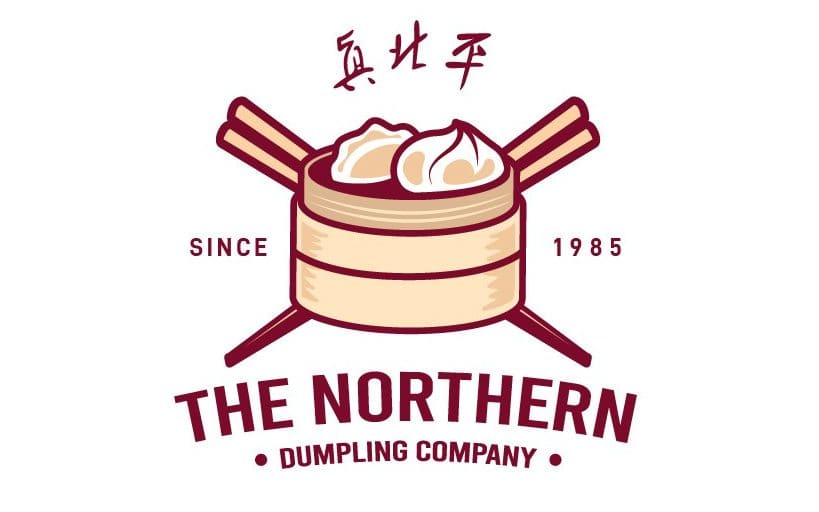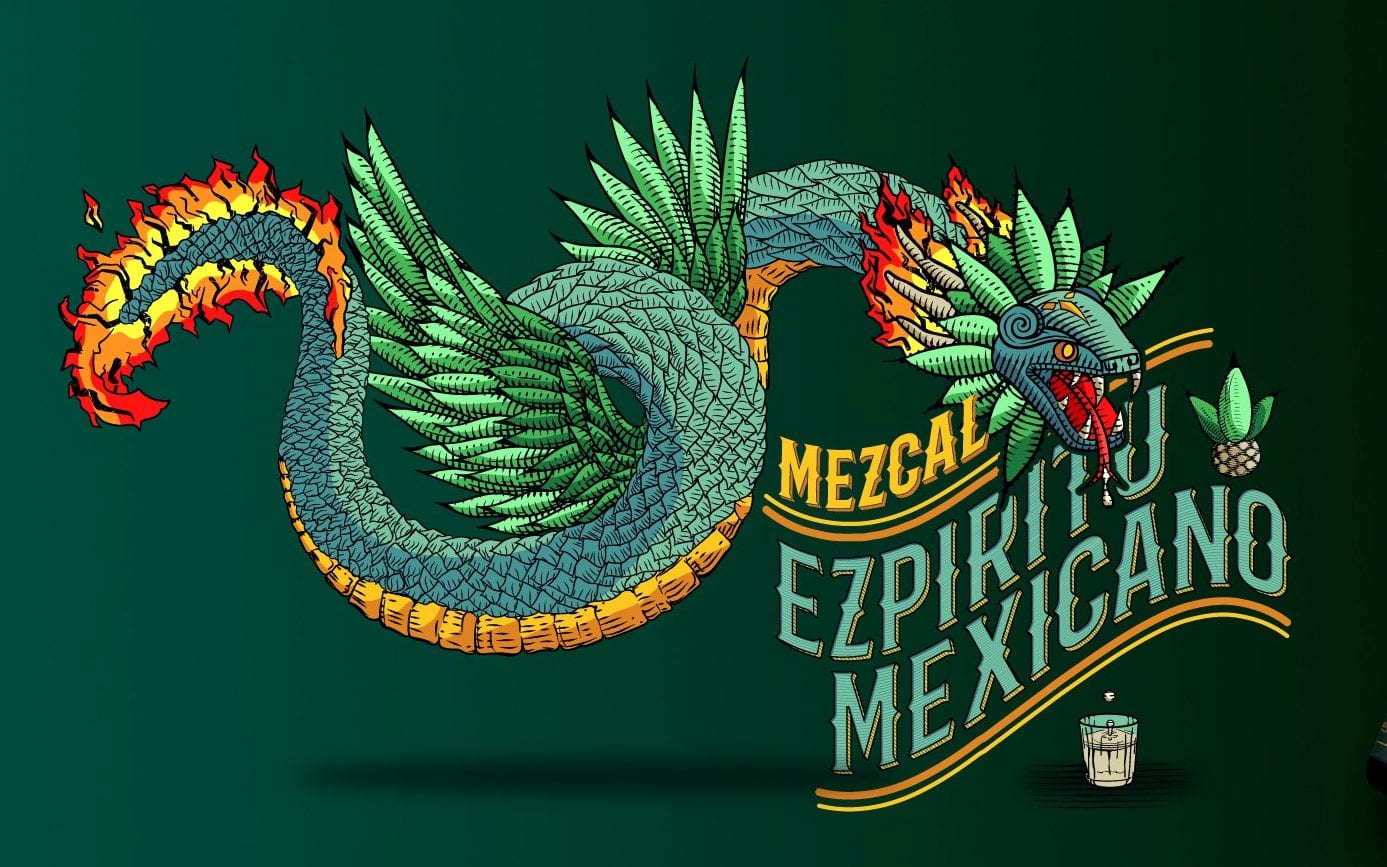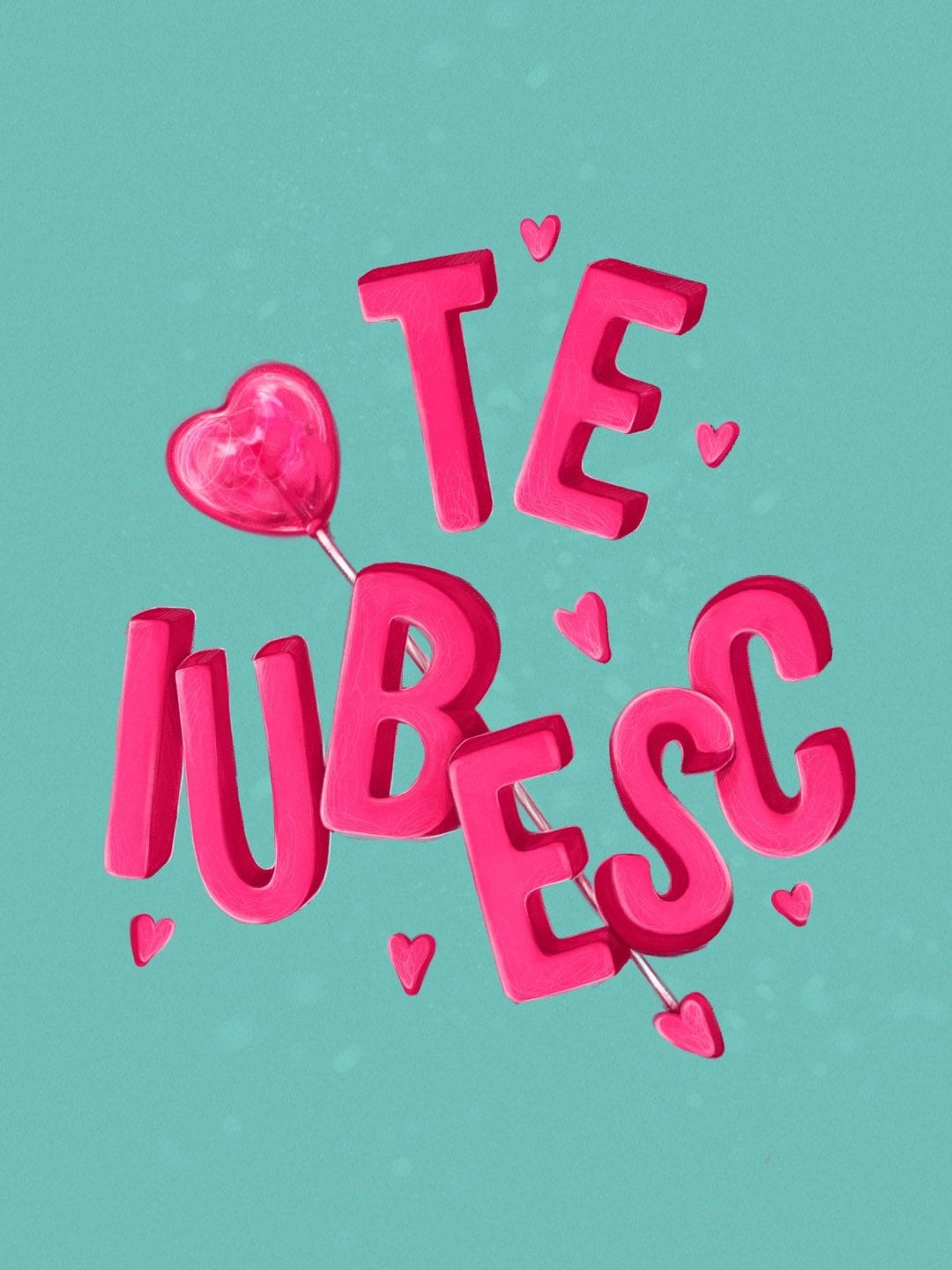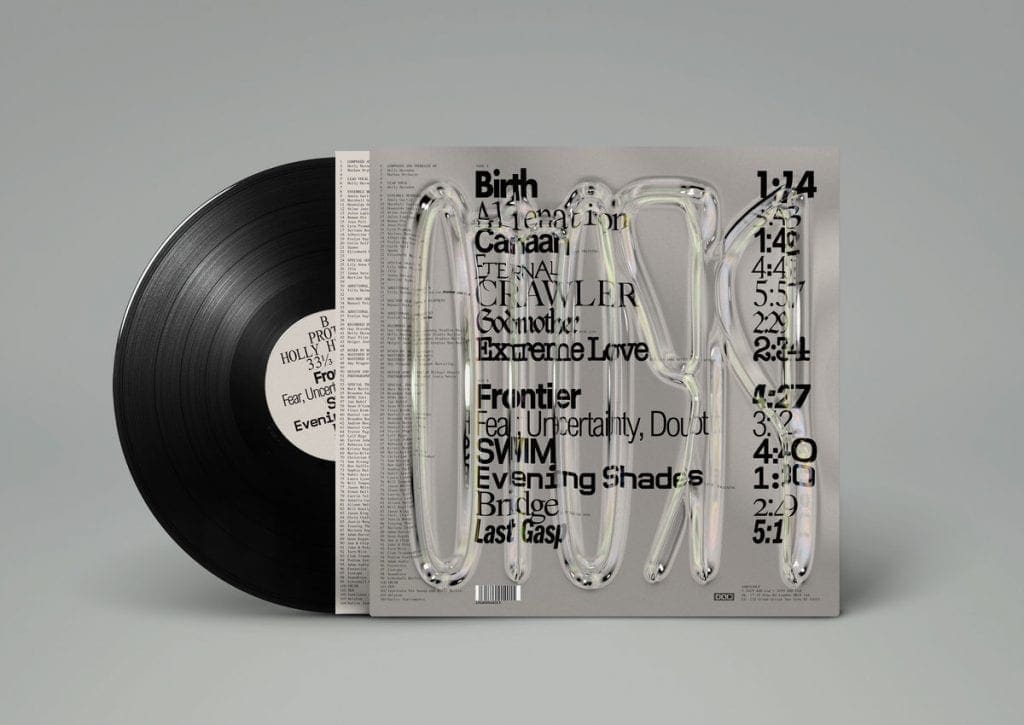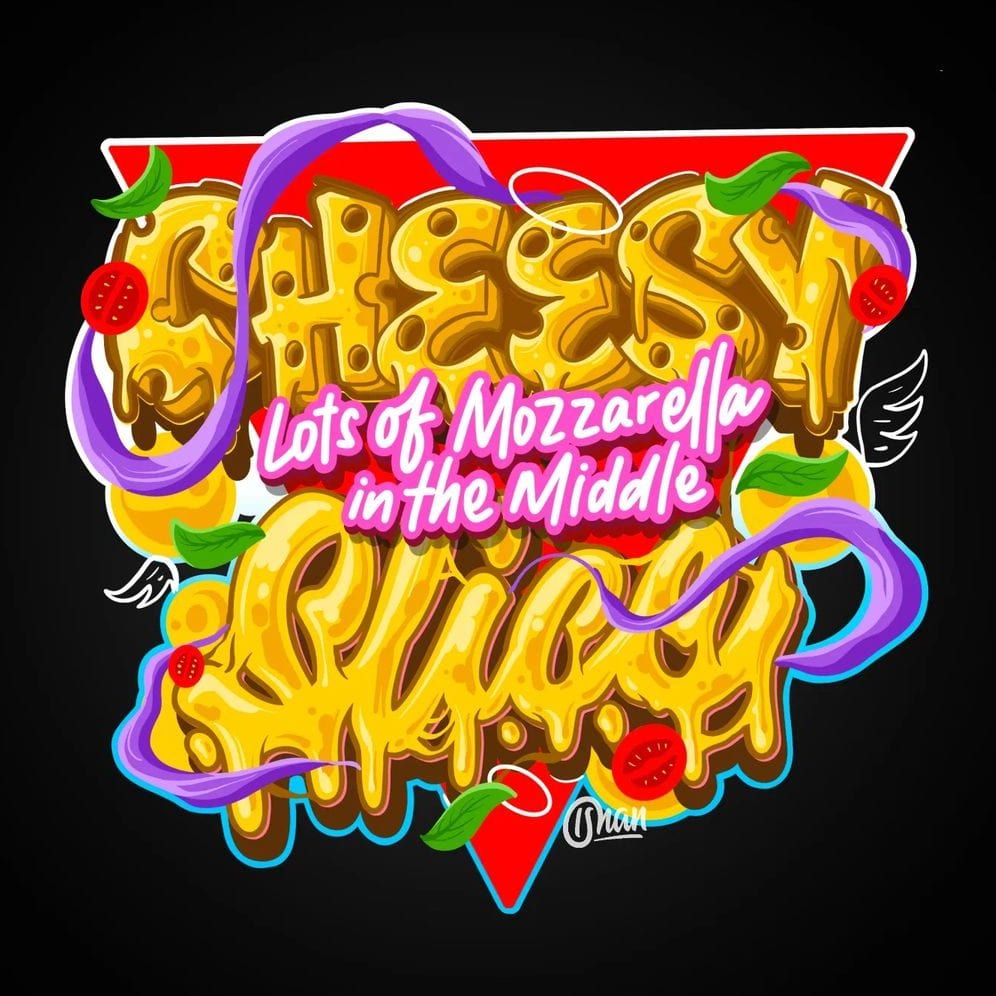
Aktuell erlebt die digitale Kunstwelt eine einzigartige Phase der Transition. Die Schriftarten-Trends für 2024 spiegeln das wider. Vor dem sich schnell ändernden Hintergrund aus maschinellem Lernen und generativer KI haben sich viele Schriftartenentwicklerinnen und -entwickler auf traditionelle handschriftliche Techniken zurückbesonnen. Gleichzeitig treibt eine neue Designergeneration die Schriftarten in kreative Extreme: mit Buchstaben, die sich bewegen, Platz beanspruchen und ins Abstrakte abdriften.
Wir stellen sieben Schriftarten-Trends für das Jahr 2024 vor – unabhängig vom Designansatz entspringen sie alle der Kreativität von Typografinnen und Typografen im beispiellosen digitalen Zeitalter. Ob Sie einen neu aufgelegten Retro-Stil bevorzugen oder auf knallige Experimente setzen möchten, diese Schriftarten sprechen Leserinnen und Leser weit über die geschriebenen Worte hinaus an. Und sie bieten Kleinunternehmen neue Möglichkeiten, Ihre Marke oder Perspektive auf diese neue Welt visuell umzusetzen.
Top 7 Schriftarten-Trends für 2024
1. Ultra Gothic
Fraktur-Schriftarten sind wahre Klassiker. Sie wurden im Mittelalter für handschriftliche Abschriften entwickelt. Die traditionelle Fraktur besteht aus dicken schwarzen Buchstaben und zeichnet sich durch Kalligrafietechniken wie Schnörkel (den sogenannten Elefantenrüssel) und kantige Striche aus. Die an die Spitzbögen mittelalterlicher Klöster erinnernden Fraktur-Schriftarten erfreuen sich anhaltender Beliebtheit. Erst im letzten Jahr wurde der „Ultra Gothic“-Trend massentauglich und heute erfährt er einen neuen Boost.
Beim „Ultra Gothic“-Trend 2024 verwenden Designerinnen und Designer digitale Hilfsmittel, um Effekte zu erzielen, die mit der klassischen Schriftartenkreation nicht möglich waren. Übertriebene Striche und Linien halten mit der faszinierenden mittelalterlichen Architektur Schritt und komplexe Schnörkel grenzen an Unleserlichkeit. Fraktur-Schriftarten sind zeitlos attraktiv aufgrund ihres charakteristischen Stils, der stabile Formen mit unerwarteten Freihandstrichen kombiniert, was digitalen Schriftarten einen persönlichen Touch gibt. Und obwohl die Fraktur-Schriftarten Konnotationen aus der alten Welt mitbringen, passen ihre abenteuerlichen Schnörkel doch perfekt in Magazin-Typografie und Logodesign-Schriften.
„Neo Gothic ist bereits ein Trend in der Architektur und Literatur und gewinnt im zeitgenössischen Design an Bedeutung, wo er durch die Verwendung von Ornamenten, Schwarzschrift und Kalligraphie in wundervolle Schriftbilder umgesetzt wird. Dieser Stil passt zu High-End-Produkten und Luxusmarken. Er kann aber auch cool und urban umgesetzt werden, zum Beispiel kombiniert mit Graffiti- und Street-Art-Elementen.“
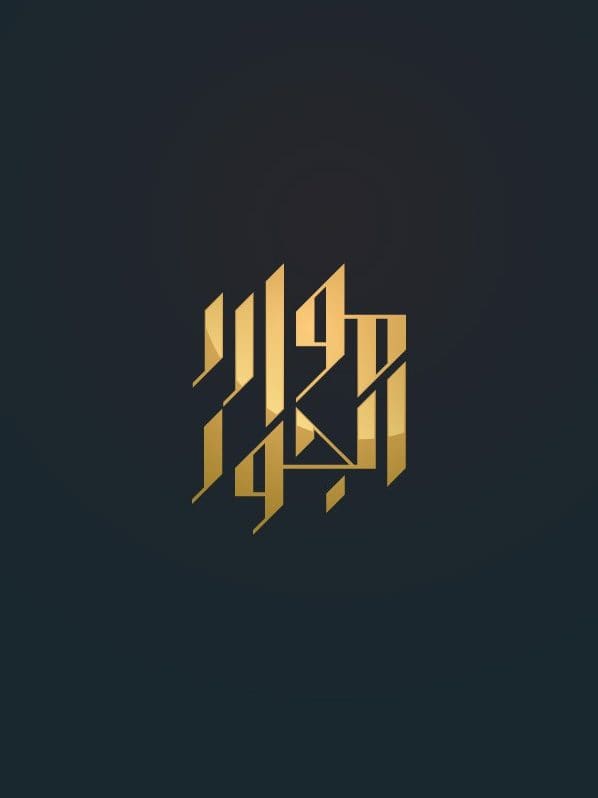
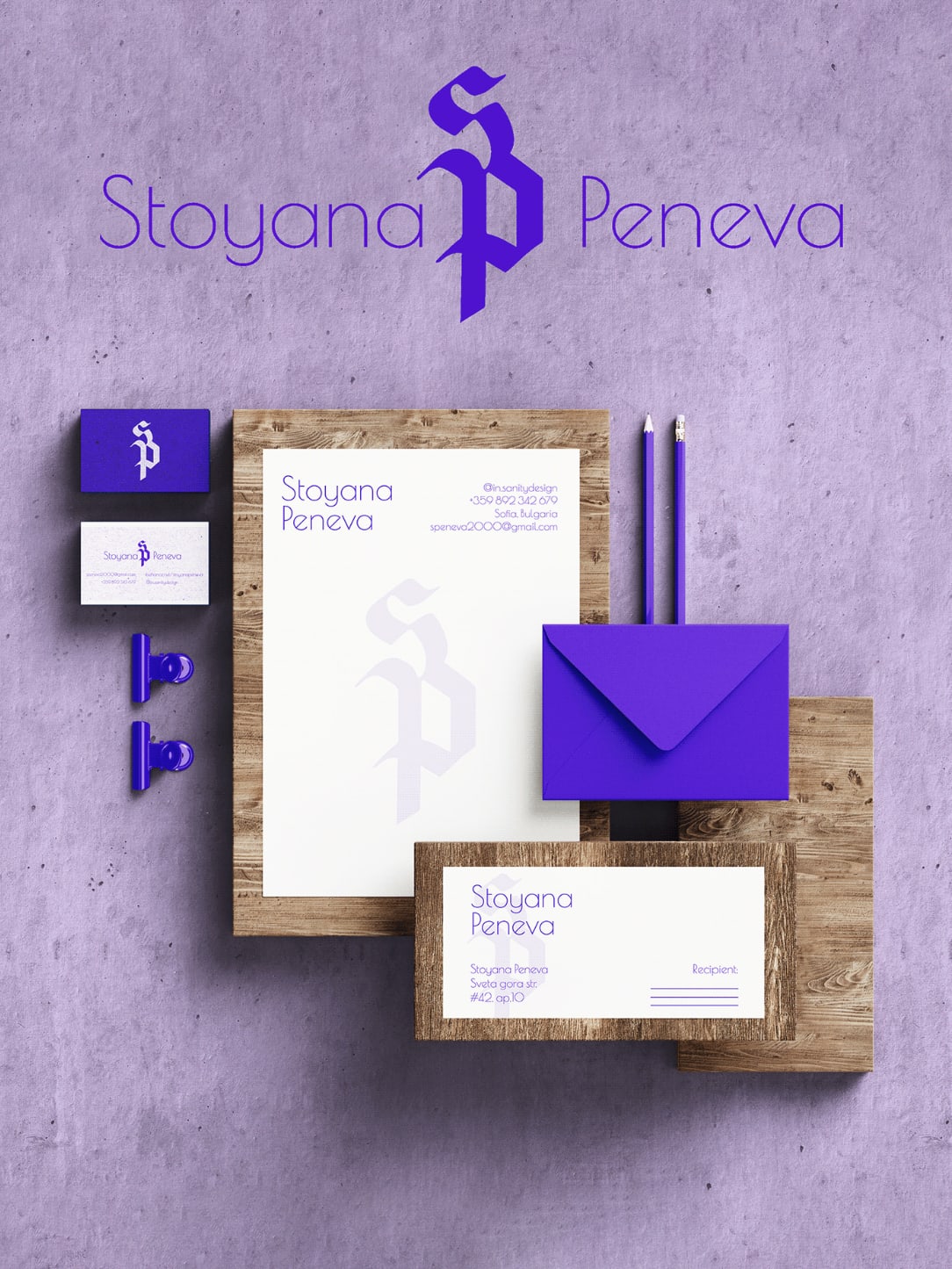
2. Formverändernde Buchstaben
Was wir aus der Tatsache lernen, dass Schriftartendesignerinnen und -designer aus ein und demselben Alphabet unendlich viele Buchstabenvariationen zaubern können, ist, dass Buchstaben unglaublich wandelbar sind. Und 2024 werden wir Schriftarten entdecken, die ihre Form direkt vor unseren Augen verändern.
Der Trend der formverändernden Buchstaben ist von Retro-Quellen inspiriert, wie Rubberhose-Schriften und Comic- und Cartoon-Styles aus den 70ern. In diesem Sinne ruft der Trend nostalgische Gefühle hervor und erweckt die Vergangenheit durch fließende Bewegungen zum Leben. Die schmelzende Form der wabbeligen Buchstaben deutet an, dass hier etwas nicht stimmt – eine leicht verzerrte Realitätsflucht.
Dem Eskapismus wohnt eine Spannung inne, denn auch wenn er uns an einen glücklichen Ort aus der Vergangenheit entfliehen lässt, impliziert das Bedürfnis nach einer Flucht, dass es etwas gibt, vor dem man fliehen muss. Solche Schriftarten spielen mit dieser Spannung in einem comicartigen Cartoon-Style und machen den Trend damit für provokantere Kontexte beliebt, wie Poster für Musikevents, Streetwear und Protestkunst.
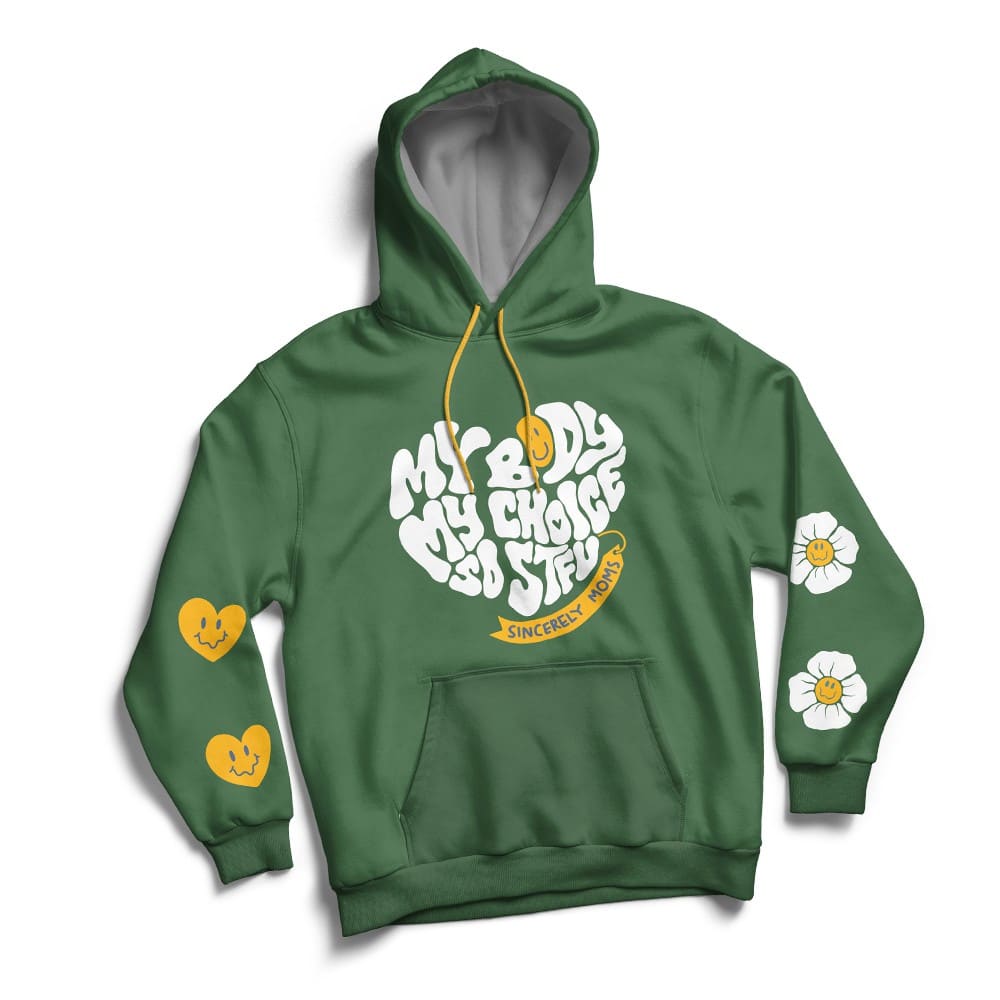
Quelle: yogisnanda über 99designs von Vista.
Quelle: DR3 über Dribbble.
„Ich liebe diesen Stil! Er bringt die Botschaft rüber. Eine Kombination aus Cartoon-Design mit moderner Typografie.“
Yogi Isnanda, Designer bei 99designs von Vista
3. Feine serifenlose Schrift
Wenn wir an feine Schriftarten denken, kommen uns häufig Schreibschriften in den Sinn: weiche, geschlungene Kursivschriften, die oft auf Hochzeitseinladungen zu finden sind. Serifenlose Schriftarten sind dagegen gerade heraus und funktional, reine Buchstabenformen ohne Veredelung. 2024 zeigen sich serifenlose Schriftarten von ihrer zarten Seite durch enge Striche und breites Kerning.
Quelle: Sepehr™ über 99designs von Vista.
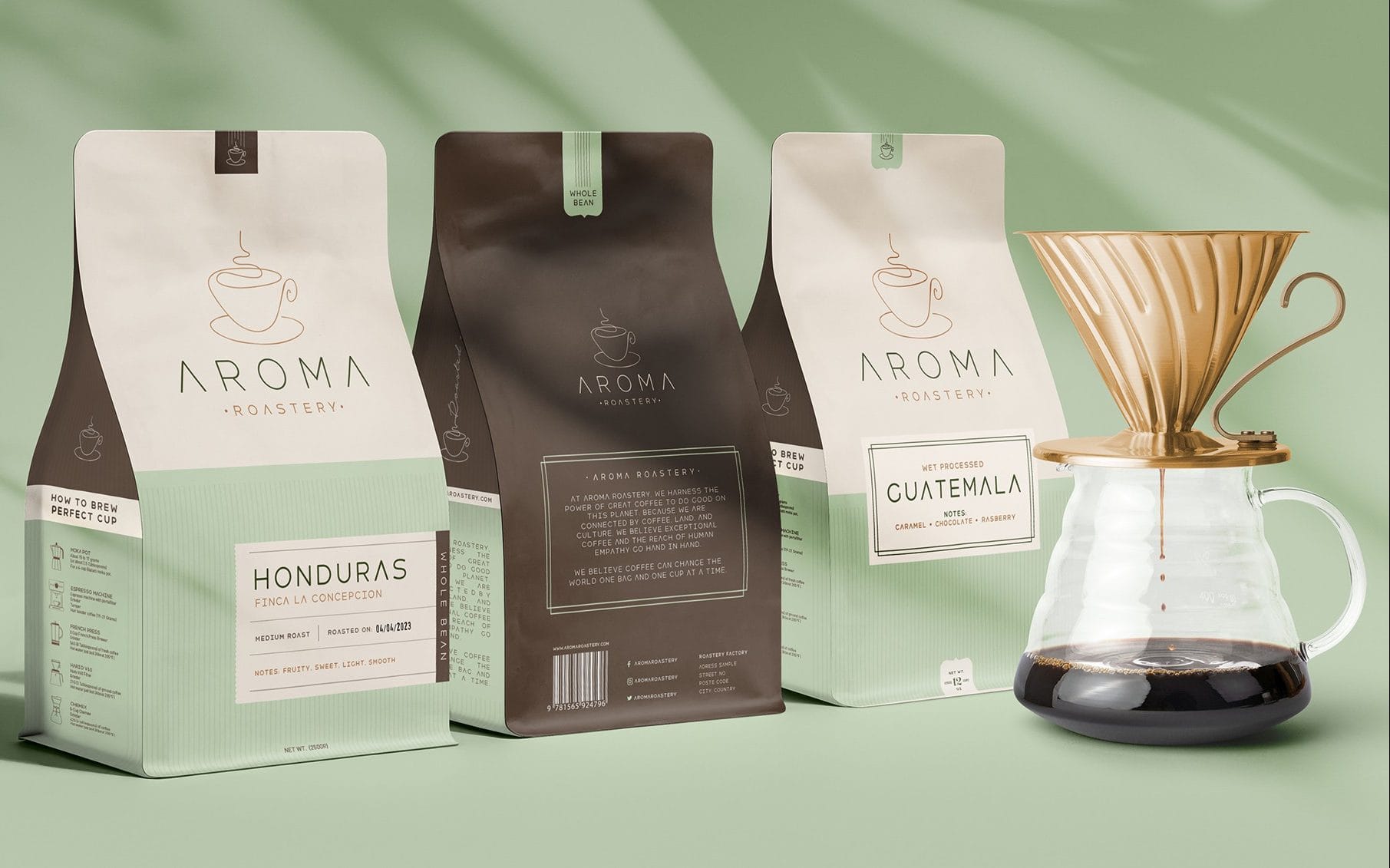
Quelle: smashingbug über 99designs von Vista.
Passend zum aktuellen minimalistischen Trend, sind feine serifenlose Schriften vielseitige Schriftarten, dank deren schlichter Formen niemals das Risiko besteht, eine Komposition zu überladen. Da sie durch ihre Subtilität Vertrauen ausstrahlen, wirken diese Schriften edel und elegant. Besonders beliebt sind diese Schriftarten bei Verpackungen aus dem Wellness-Bereich und Monogramm-Logos, wenn eine entspannte Atmosphäre entstehen soll, die professionell und elegant wirkt.